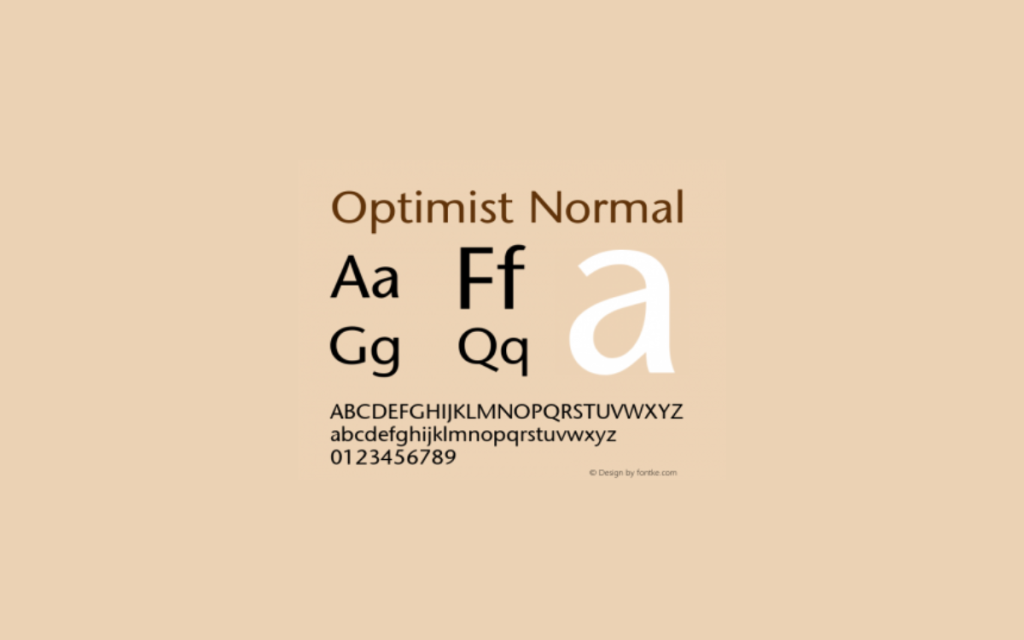
Optimistic Font
Ngôn ngữ: Tiếng Việt, Tiếng Anh
Việt hóa: Việt Hóa
Bộ Font: Font Optimistic
Phân loại: Vui tươi
Độ dày: Regular, Bold
Optimistic Font là thuật ngữ thường được dùng để chỉ những kiểu chữ mang đến cảm giác vui tươi, tích cực và đầy năng lượng. Những font chữ này thuộc bộ font chữ không chân, thường có đường nét mềm mại, uốn lượn hoặc có nét bo tròn tạo cảm giác ấm áp và thân thiện. Một số font chữ có thể kết hợp thêm các yếu tố như màu sắc tươi sáng hoặc các ký tự được thiết kế độc đáo để truyền tải thông điệp lạc quan và khuyến khích sự sáng tạo. Sử dụng “optimistic font” trong thiết kế có thể giúp tạo nên bầu không khí vui vẻ và thúc đẩy tinh thần, rất phù hợp cho các dự án liên quan đến trẻ em, giáo dục, hoặc các chiến dịch truyền thông mang tính động viên.